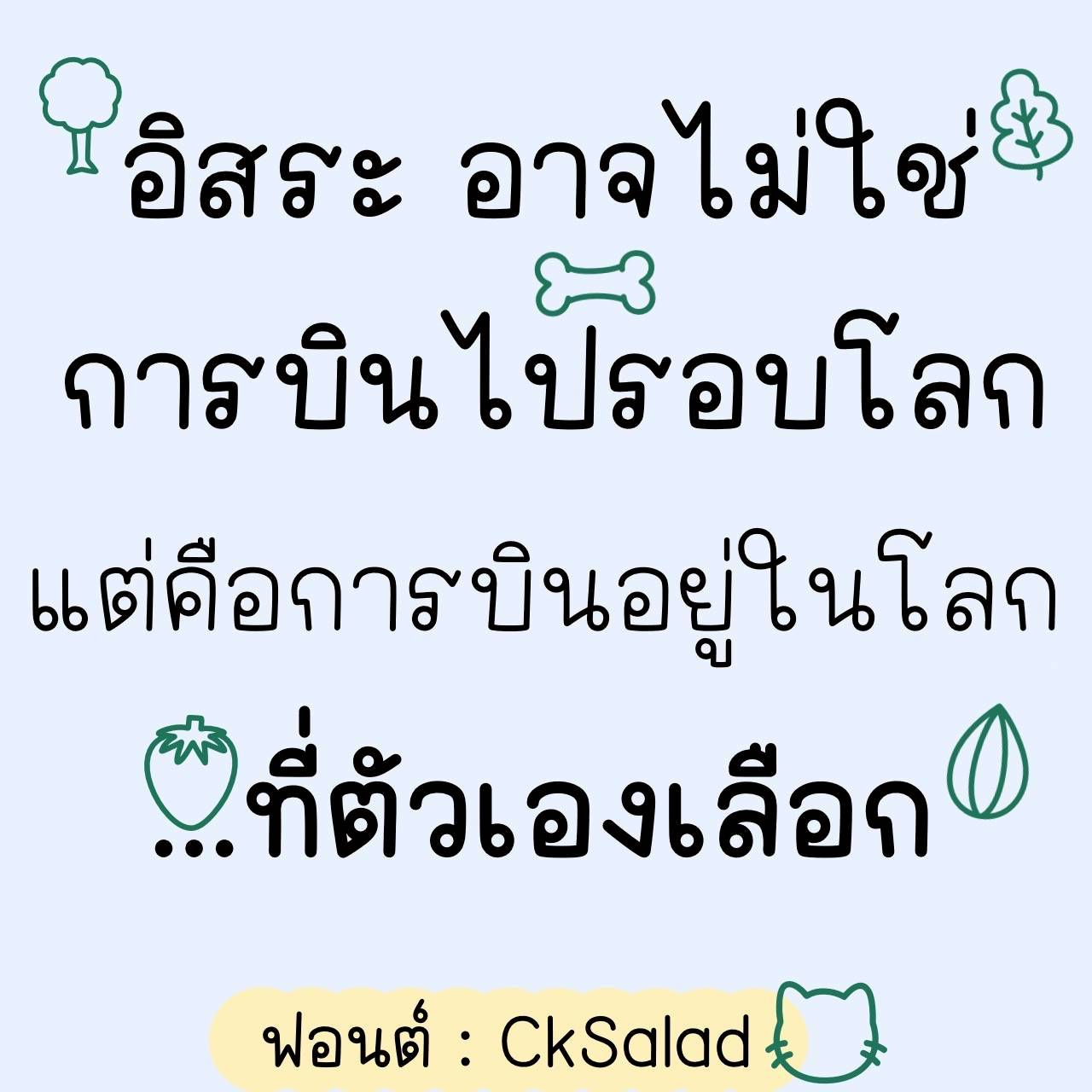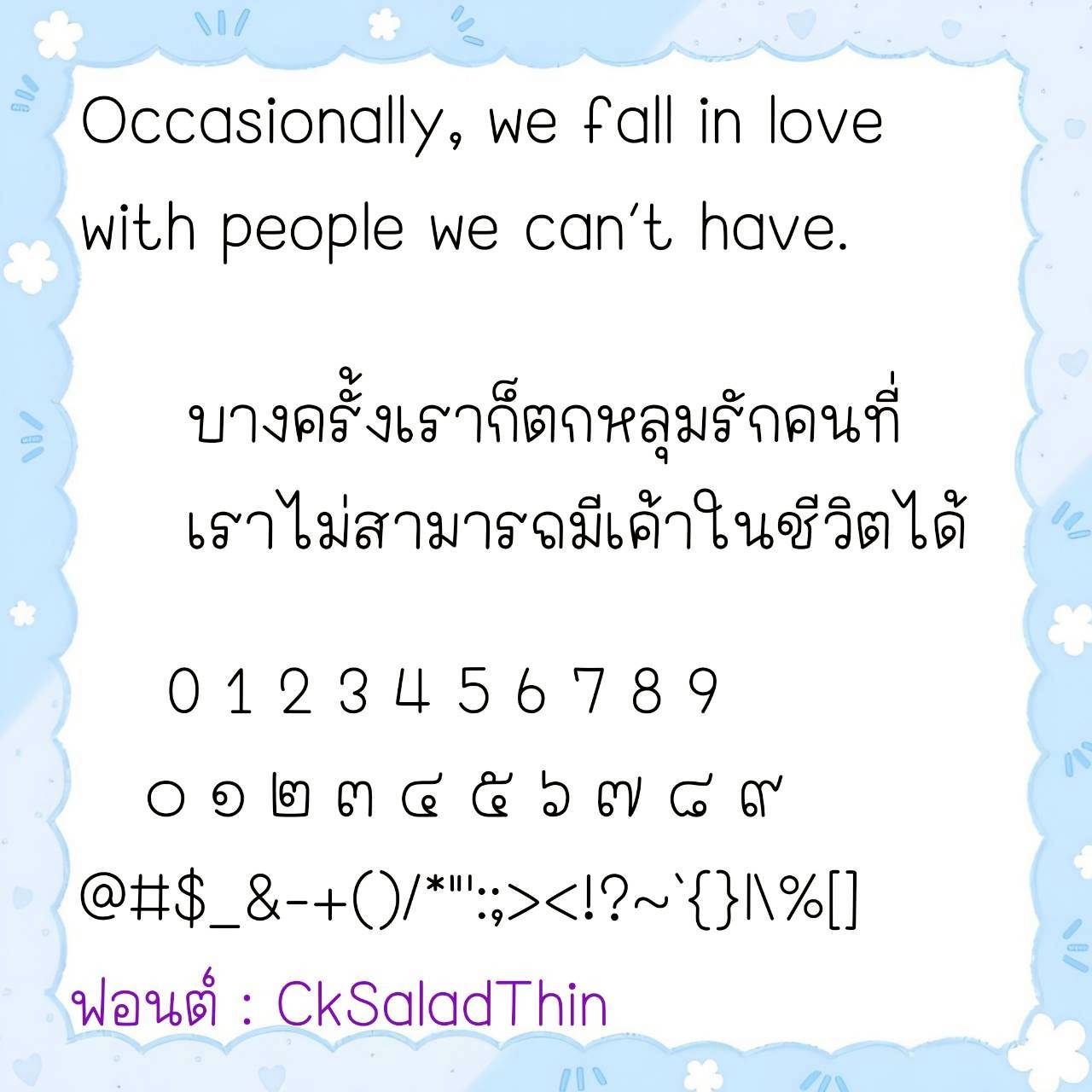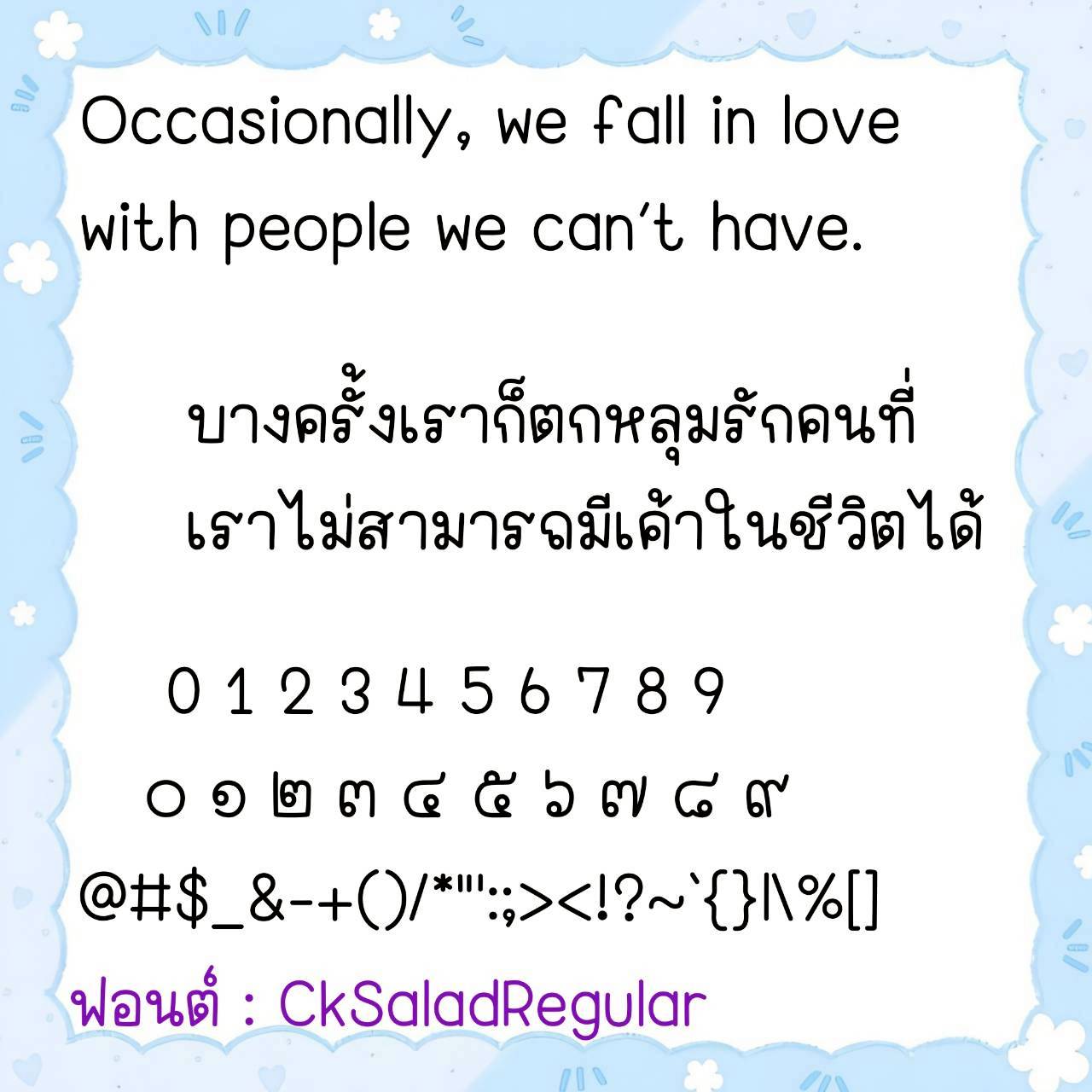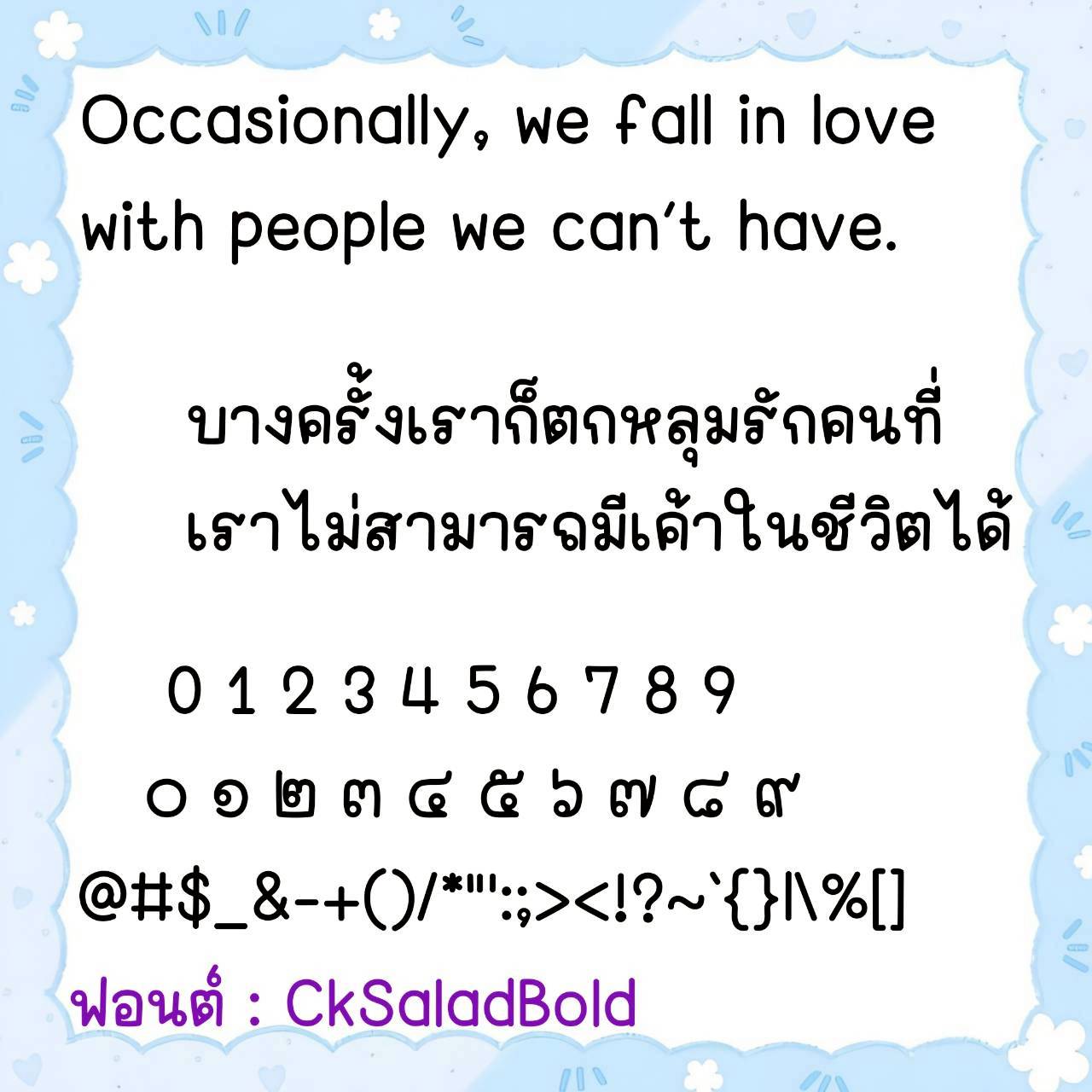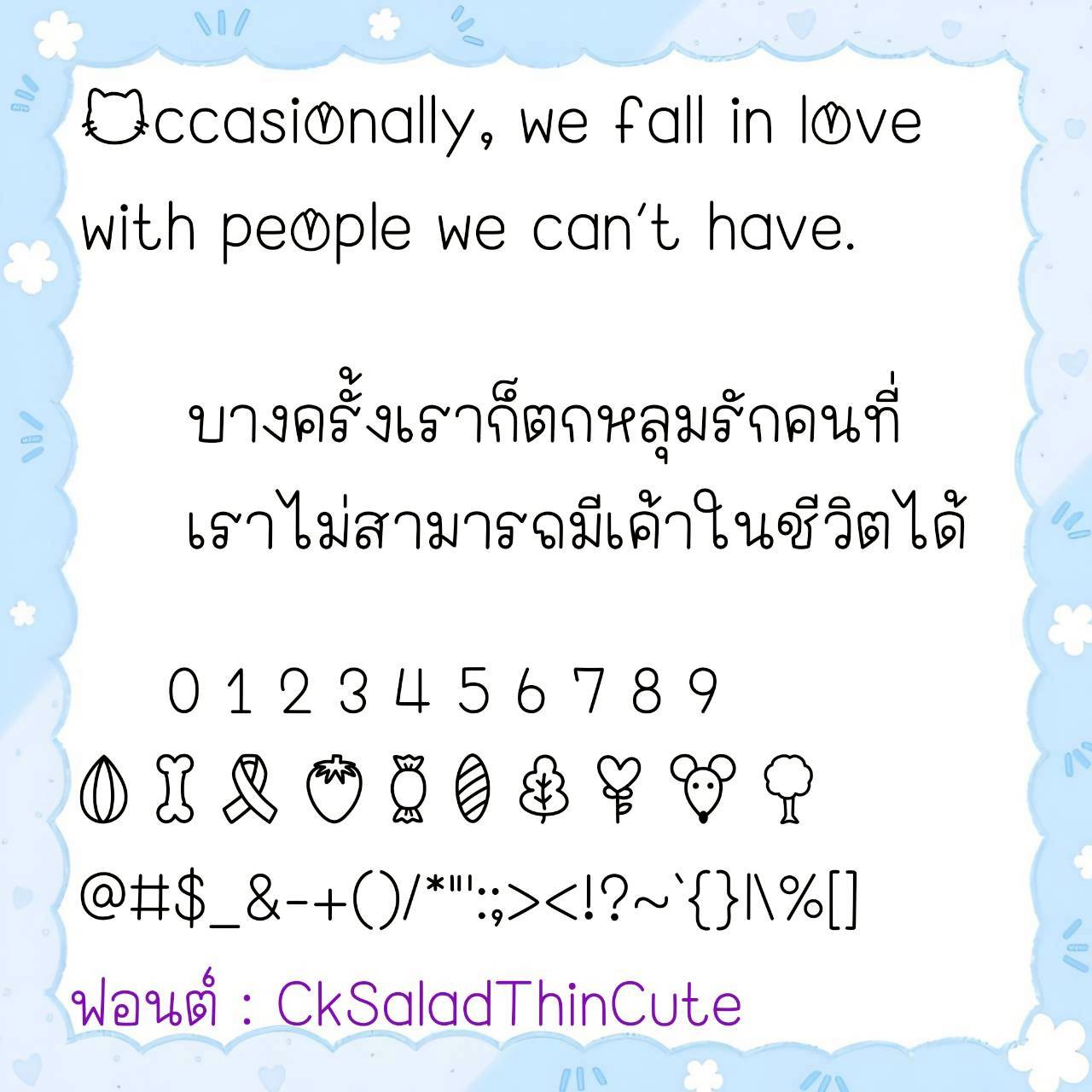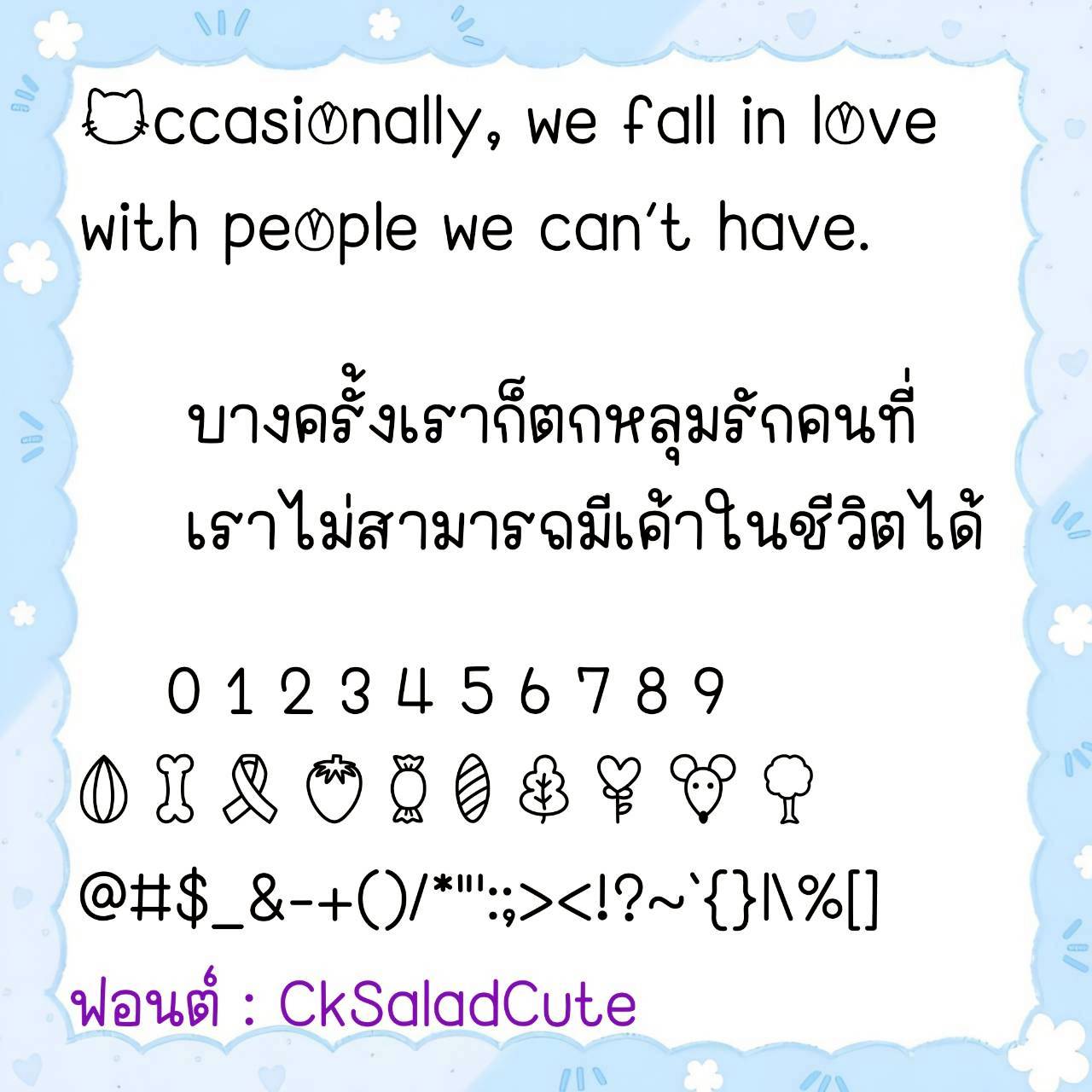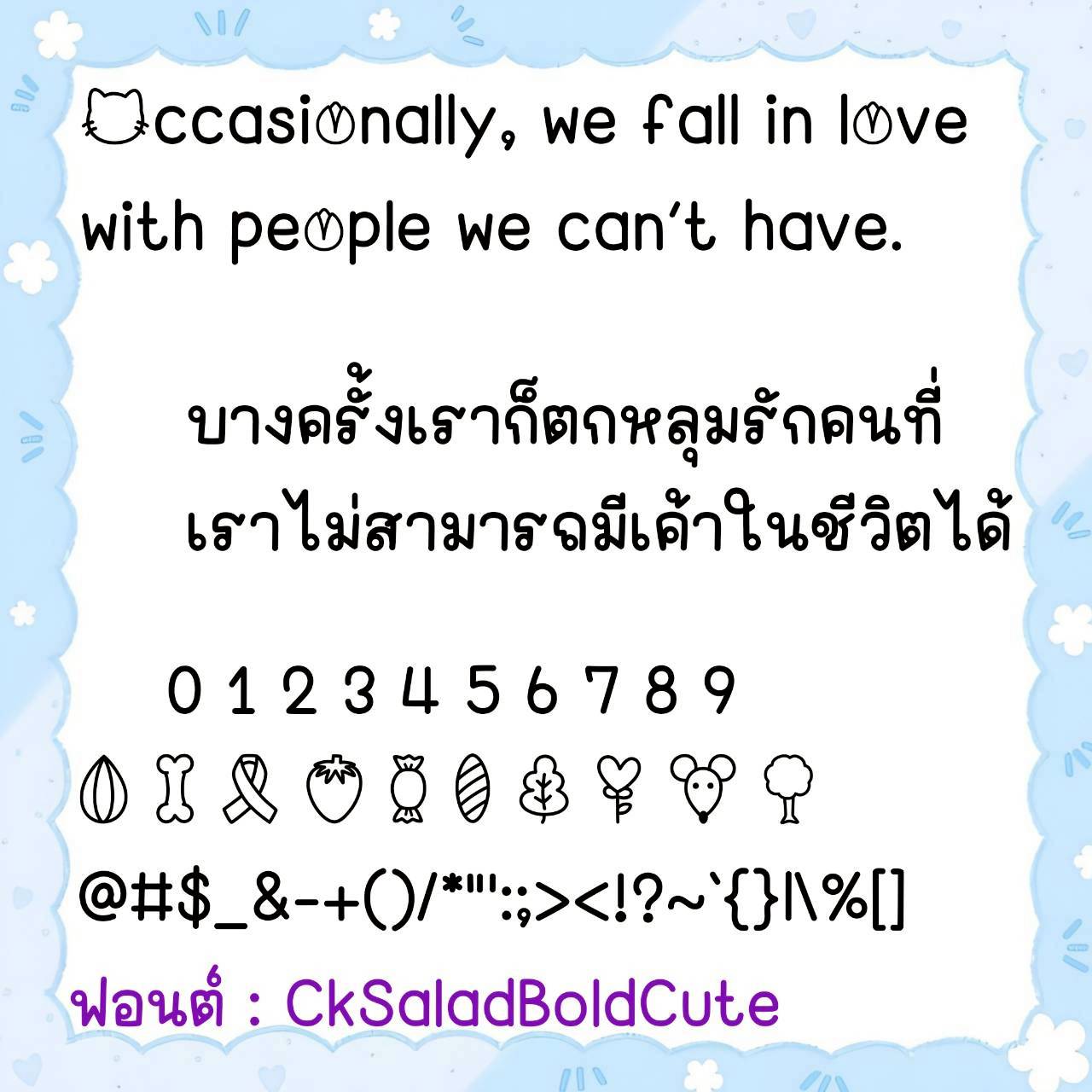
Font CkSalad
ื่อสินค้า : Font CkSalad 💙
🔸 ฟอนต์ลายมือตัวอวบอ้วน แนววัยรุ่นน่ารัก ดูมีความซนนิดๆไม่น่าเบื่อ เน้นอ่านง่ายดีต่อสายตา และยังมีไฟล์อิโมจิน่ารักๆที่ใช้แทนเลขไทยให้ด้วยค่ะ 🥰💙
🔹 A chubby, handwritten font in a cute, youthful style with a playful touch that’s not boring. It’s easy to read and pleasing to the eye, and it also includes cute emojis to replace Thai numerals. 🥰💙